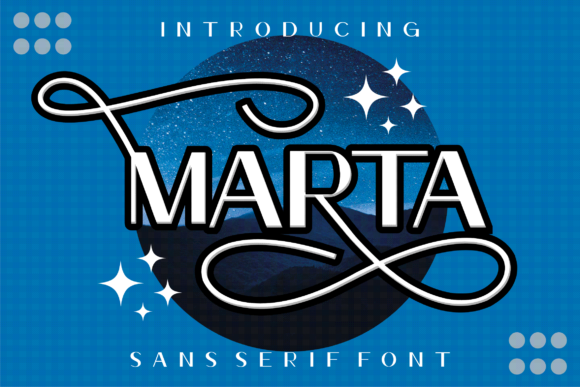
Marta - классный и выразительный шрифт.
Этот шрифт закодирован PUA, что означает, что вы можете легко получить доступ ко всем красивым глифам и штрихам!